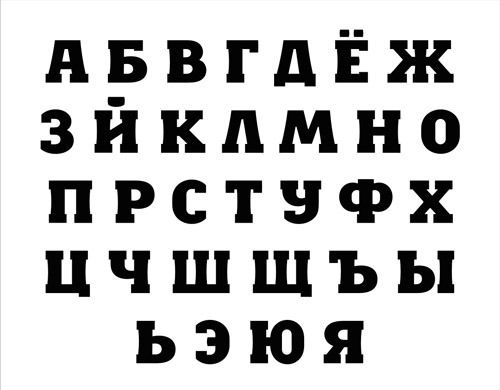
Красивые жирные шрифты русские
Красивые толстые русские и жирные кириллические шрифты, которые можно скачать бесплатно, обзор сервиса с русскими жирными шрифтами и не только.
» Русский шрифт Milano Deco. Шрифты для фотошопа » Русские шрифты.Жирный шрифт для фотошопа, Word и других текстовых и графических редакторов.
Этот генератор жирного текста примет ваши данные, которые могут состоять из нескольких слов или предложений, и создаст уникальный шрифт, который можно использовать в вашем собственном онлайн-контенте. В основе нашего инструмента лежит идея о том, что изображения всегда должны сопровождать слова. Жирные шрифты идеально сочетаются с нашими фотографиями или изображениями, поскольку они придают странице объемность и оживляют ее.
Как сделать шрифт жирным?
Это и есть жирный шрифт.
Жирный шрифт — это сильный уровень выделения. Он используется для того, чтобы выделять ключевые слова или другое важное содержание. Наш генератор полужирных шрифтов поможет вам создать идеальный шрифт для выделения вашего контента на сайте, в блогах и профилях социальных сетей.